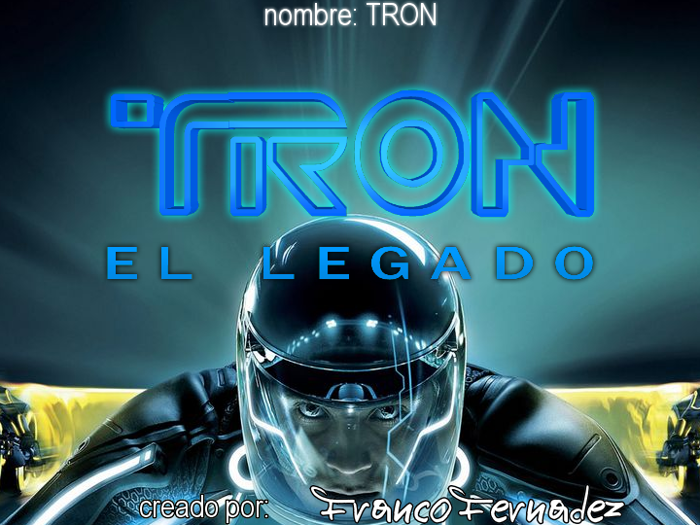
TRON Font
Fuente de La Nueva Película de Disney TRON: El Legado (TRON 2)
9 years agoTRON rocks! So does this font! All that's needed is lowercase letters.